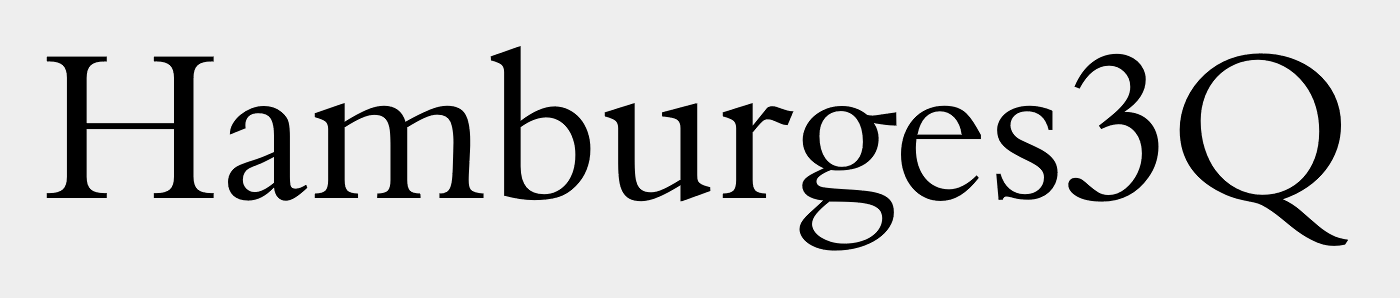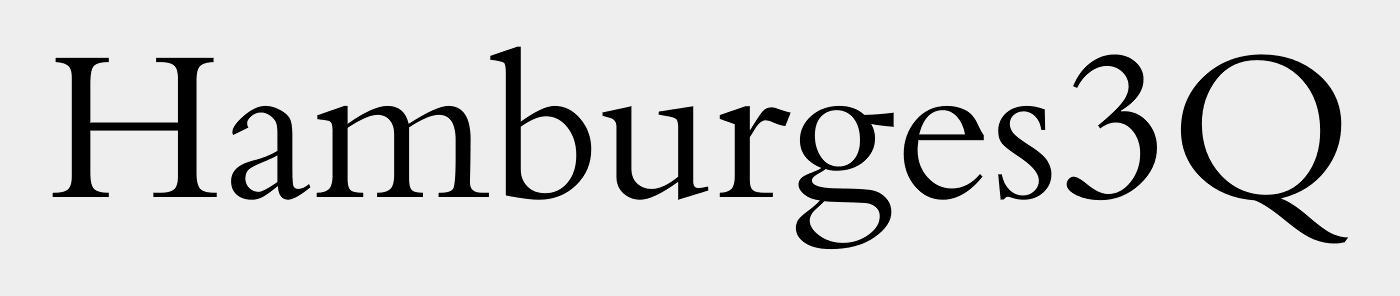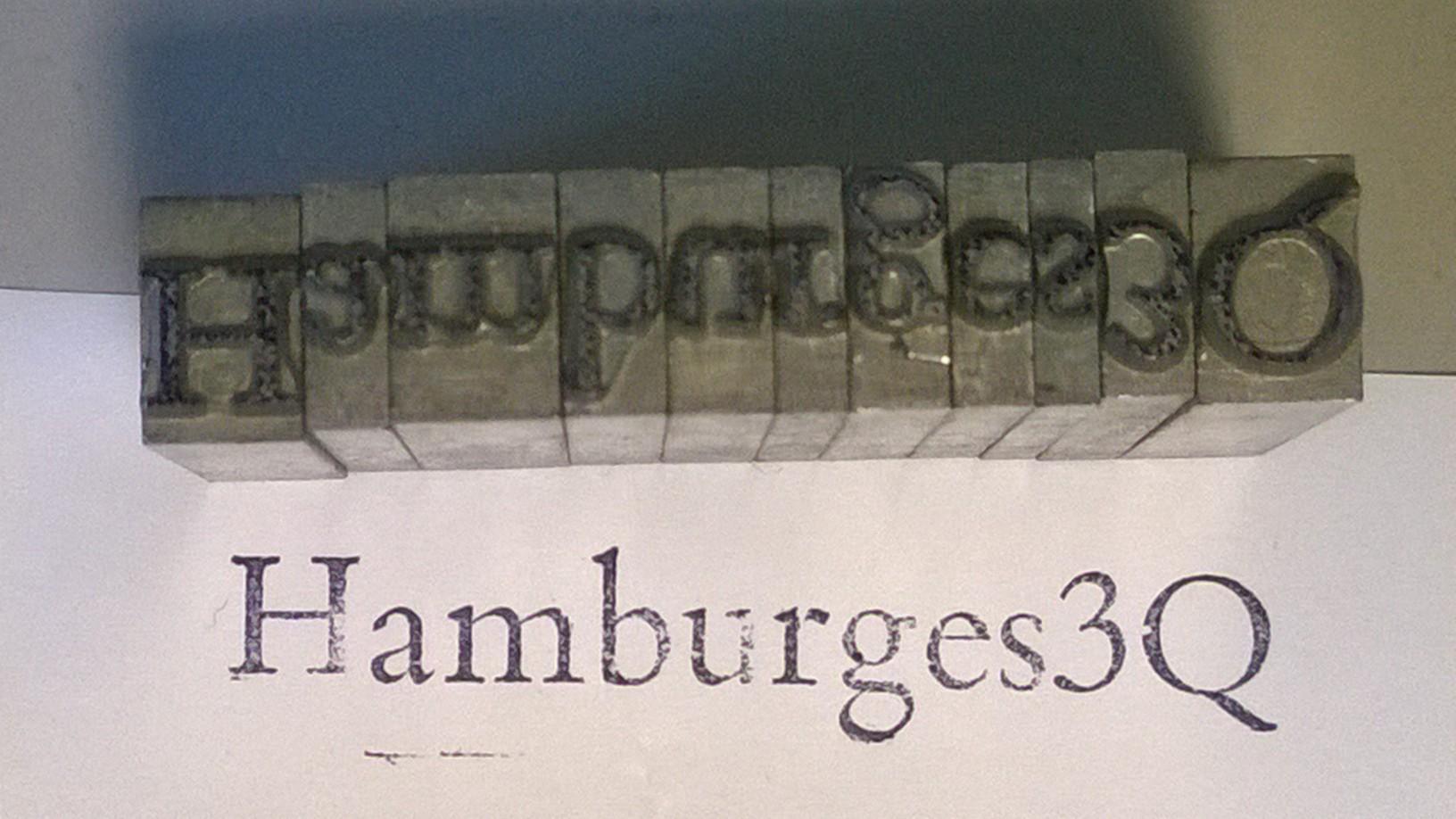
ich habe mal wieder eine unbeschriftete Schublade gefunden. Sicherlich weiss jemand, um welche Schrift es sich hier genau handelt? Sie erinnert mich an die BEMBO, aber sicher bin ich nicht... . Wer kann helfen?
Wobei dein Muster der ursprünglichen Buchdruck-Version von Monotype entspricht, da es das b mit langer Oberlänge aufweist. Bei späteren Versionen wurden die langen Oberlängen gekürzt (wie in den Beispielen von Aldine und Bembo bei myfonts).